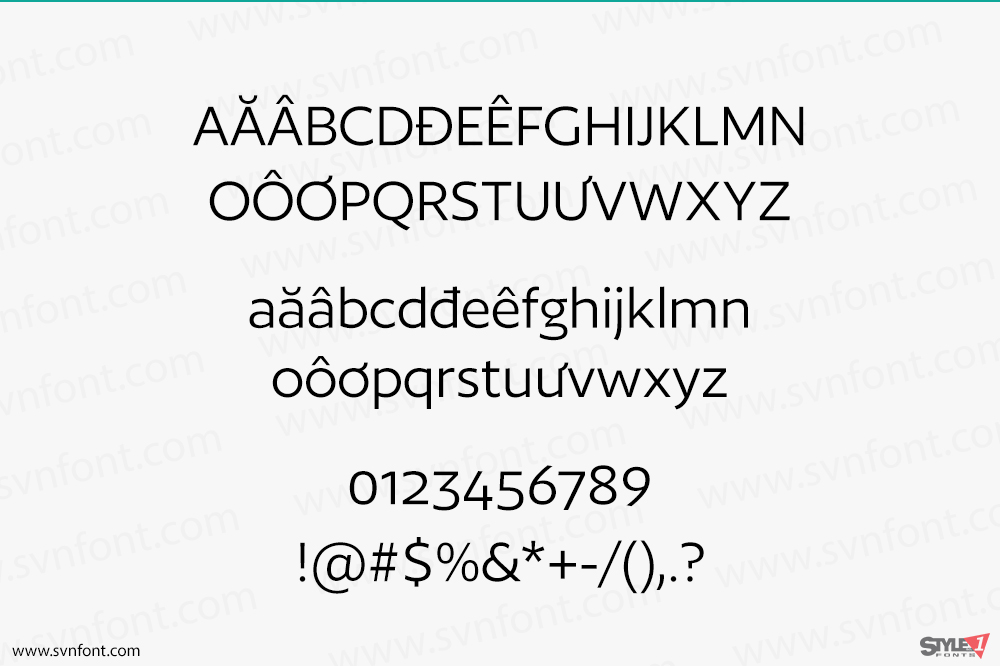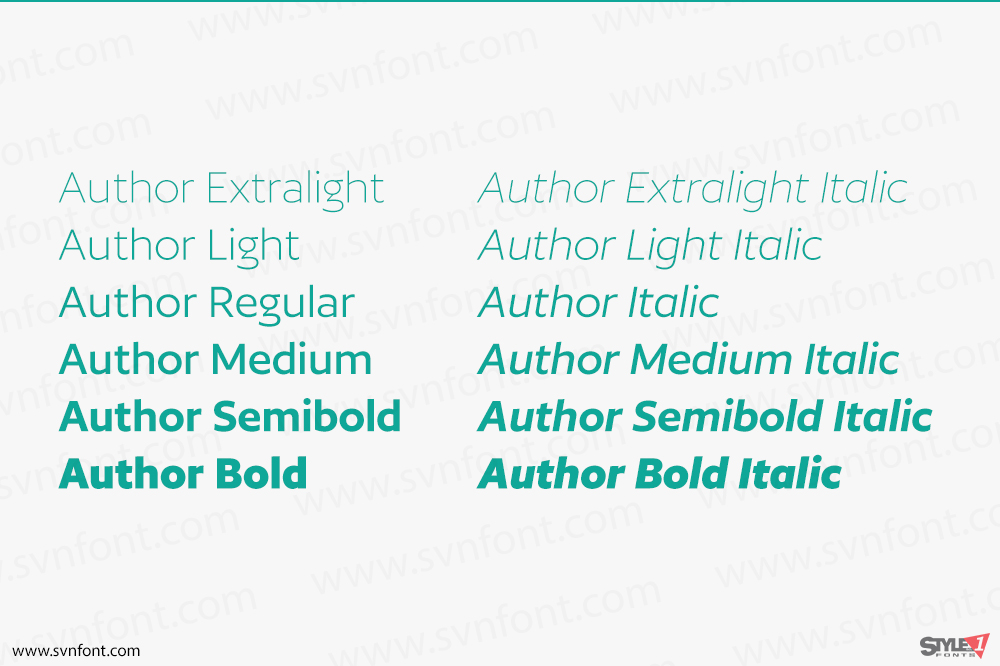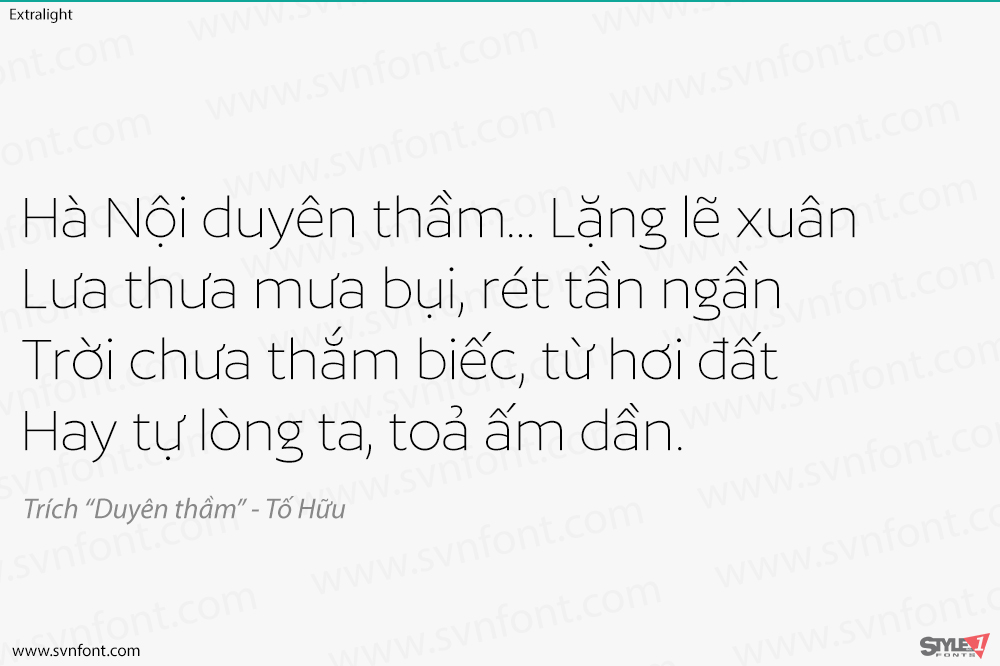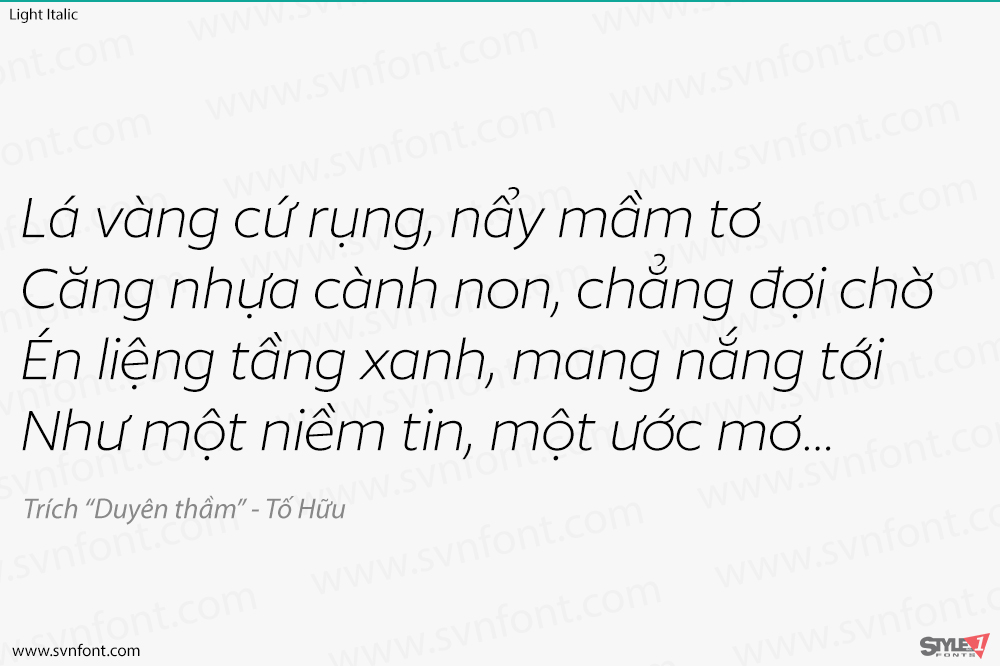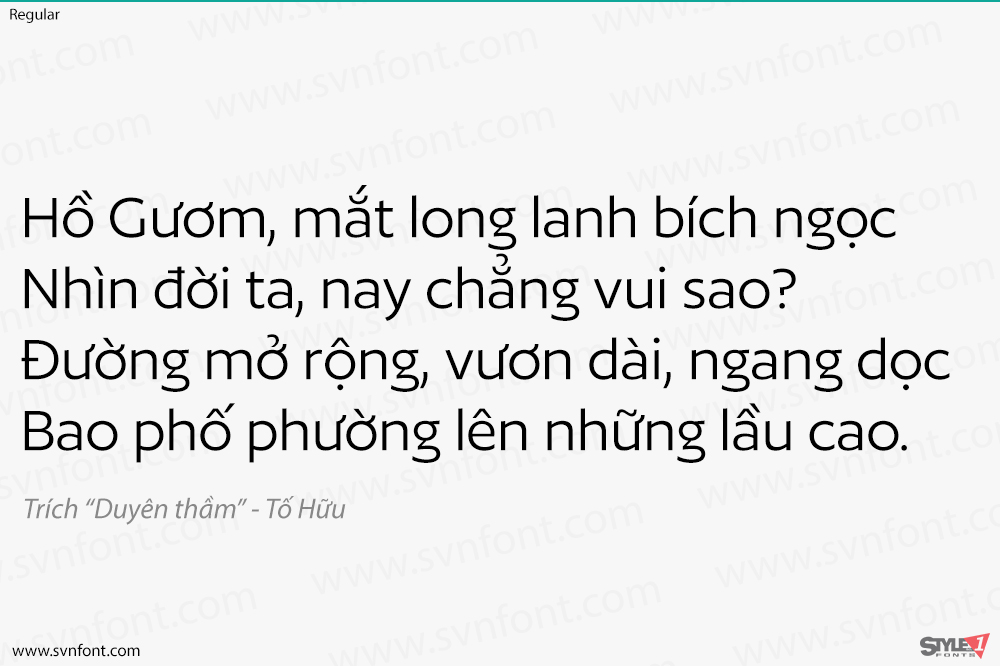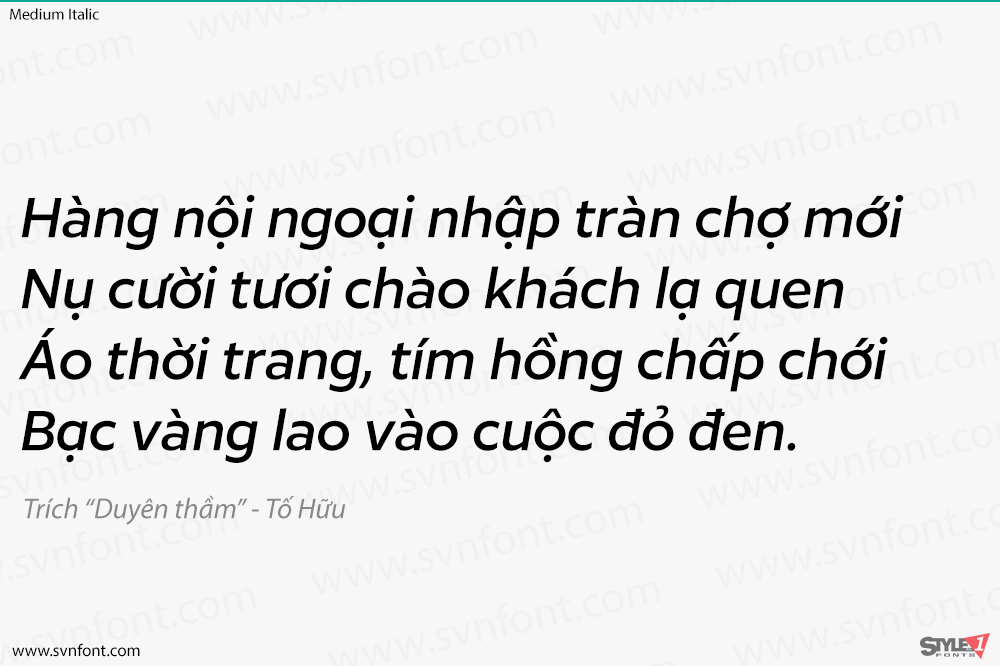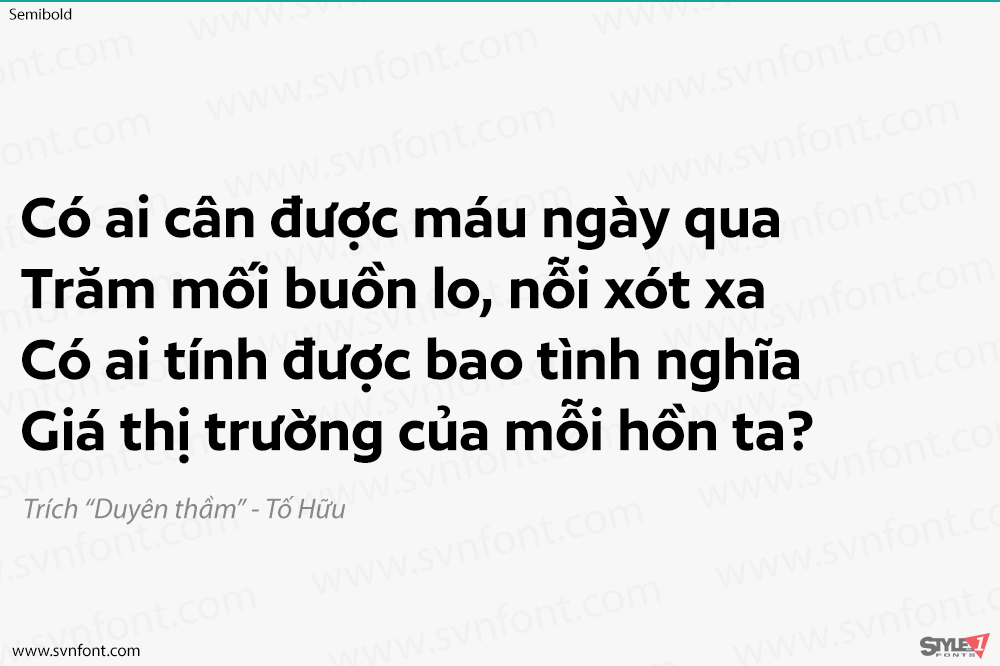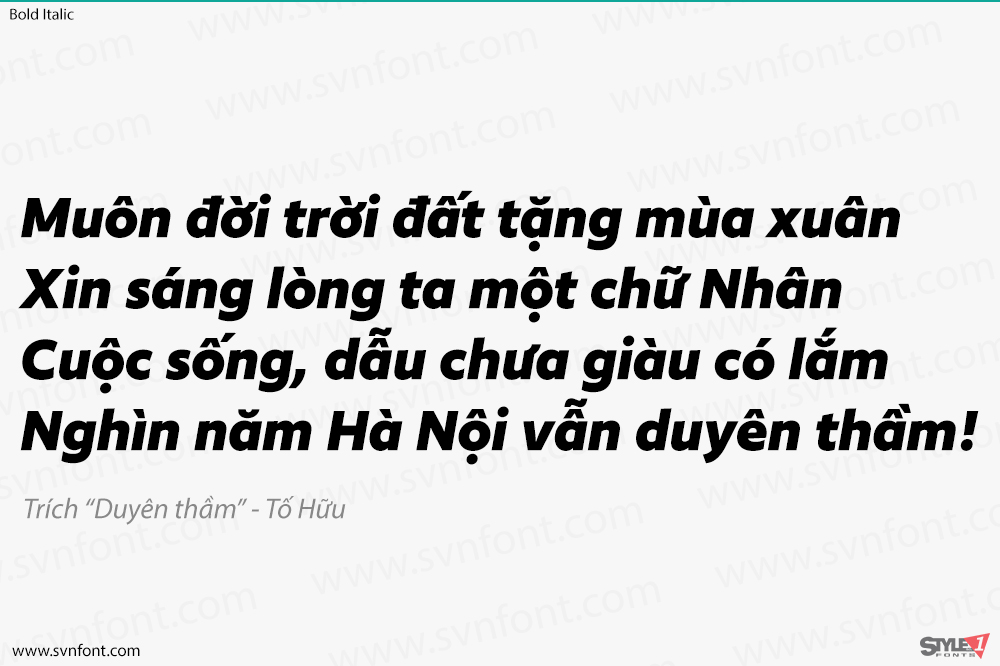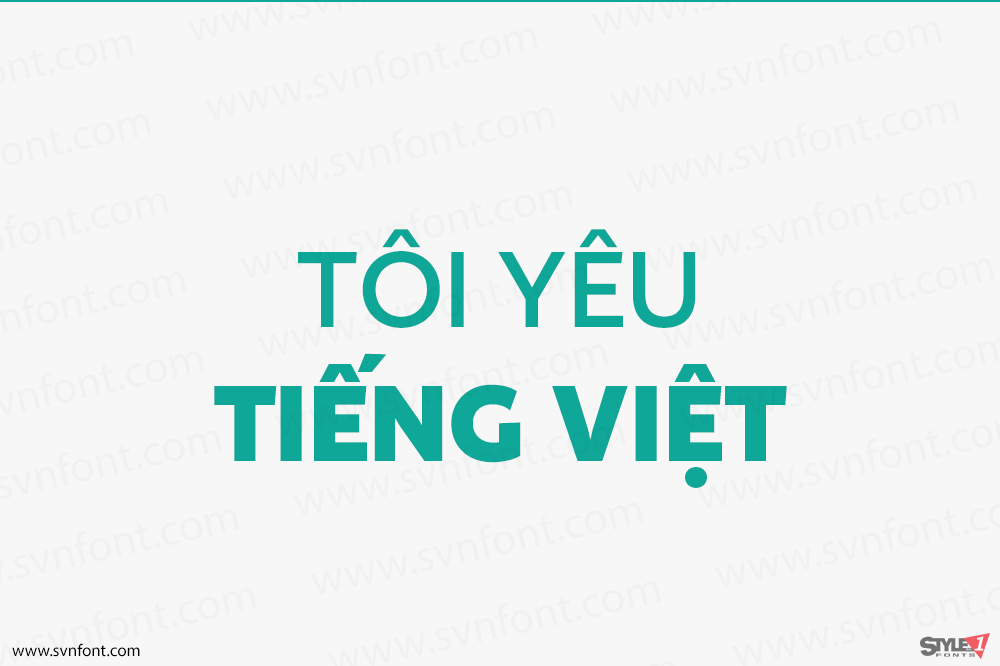
Author là một họ phông chữ sans serif humanist. Chúng được tối ưu hóa để sử dụng trong các ấn phẩm hiện đại – do đó có tên là ‘Author’ (Tác giả). Hình dáng chữ cái của nó hơi rộng hơn, tạo cho các khoảng trắng bên trong đủ không gian để “thở”, do đó làm tăng khả năng đọc và cũng giúp hiển thị tốt hơn trên màn hình. Họ phông chữ Author bao gồm sáu độ đậm, từ Extralight đến Bold. Mỗi độ đậm đều có một phiên bản đứng và một phiên bản nghiêng. Các chữ cái viết hoa có vẻ ngoài gần như đơn nét; tuy nhiên, một số chữ cái viết thường có độ tương phản nét rõ rệt. Phần đầu của các nét chữ trong Author kết thúc bằng các đường cắt chéo; chúng gợi nhớ đến bút lông rộng thường được sử dụng để viết các hình dáng chữ humanist mà kiểu chữ này dựa trên. Trong các phông chữ đứng của Author, chữ ‘a’ và ‘g’ viết thường là kiểu hai tầng; có một chữ ‘g’ viết thường kiểu một tầng trong phông chữ như một tùy chọn OpenType. Trong các phông chữ nghiêng, cả chữ ‘a’ và ‘g’ đều là kiểu một tầng. Các nét kéo dài lên trên của chữ cái viết thường trong Author cao hơn một chút so với đỉnh của chữ viết hoa. Các phông chữ của họ này bao gồm cả chữ số thẳng hàng (lining figures) và chữ số kiểu cũ (oldstyle figures); trong cả hai phiên bản, chữ số ‘3’ có đỉnh phẳng. Author đến từ Satya Rajpurohit, người sáng lập Fontshare và Indian Type Foundry.
Nhà thiết kế: Satya Rajpurohit
Nhà phát hành: Indian Type Foundry